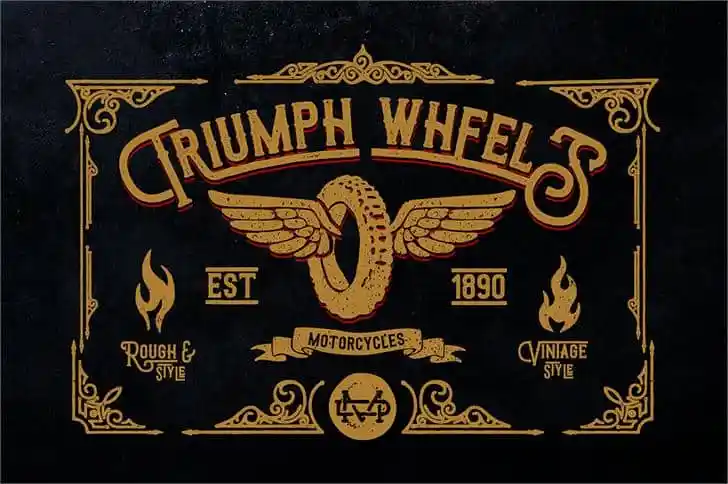
Triumph Wheels Rough Font – Download Grátis
A Triumph Wheels é uma fonte de estilo Display inspirada no estilo tipográfico americano, apresentando caracteres atraentes e modernos. Ela foi criada pelo designer madeDeduk e contém mais de 350 símbolos únicos, tornando-a uma opção perfeita para uso em aplicações diversas como design de posters, capas de livros, campanhas de merchandising, projetos de moda, newsletters, marcas de marca, anúncios, revistas e mais. Ideal tanto para designs de cartões de cumprimentos quanto para criação de texturas e citações em formatos criativos. Sua presença única e seu design atraente tornam-se uma opção indispensável para aqueles que procuram estilizar suas mensagens digitais com um toque autêntico e moderno, seja ela para uso pessoal ou profissional.